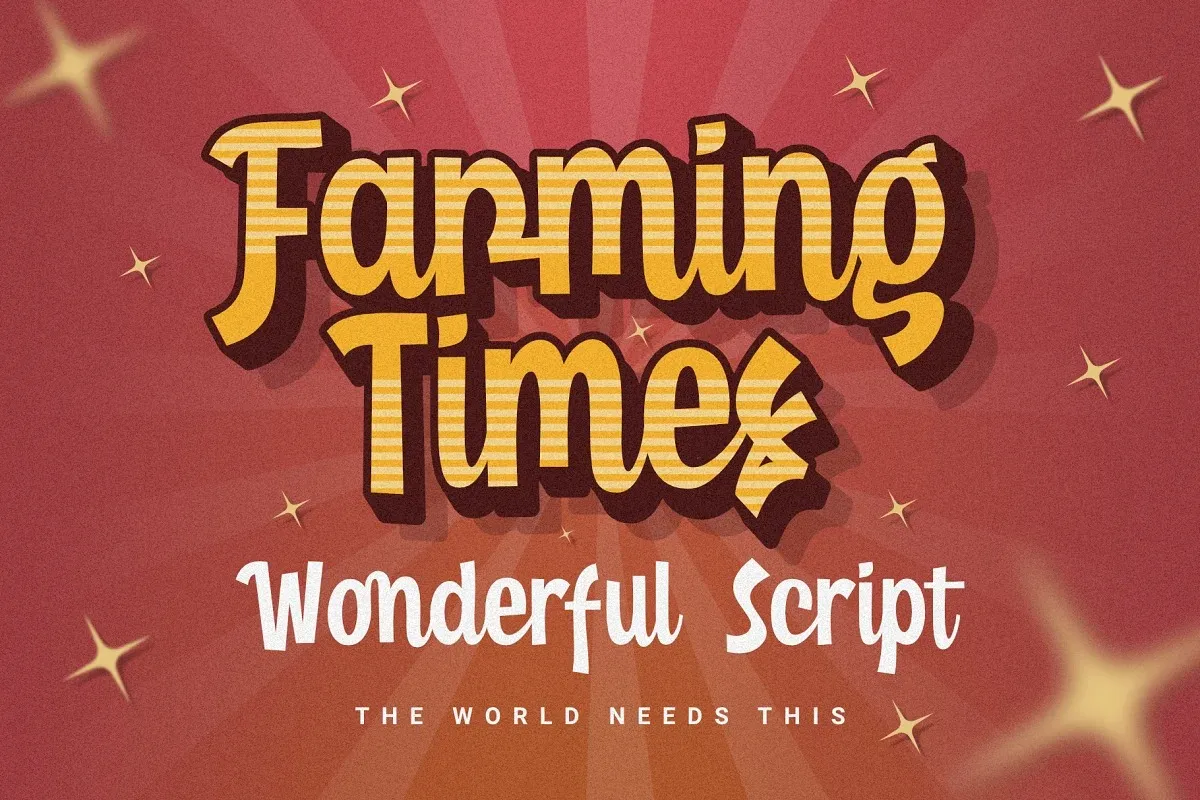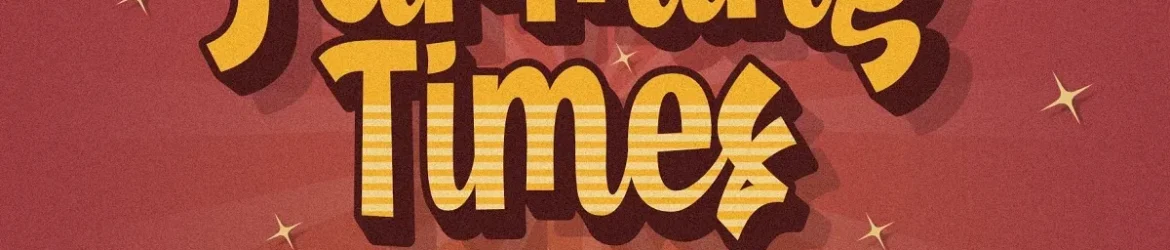
A Farming Times Font é uma elegante escolha para quem busca uma trilha sonora retro e vibrante para seus projetos de design. Este script bold tem um tom nostálgico que transporta a mente diretamente para os anos 60, oferecendo uma sensação calorosa e descontraída às criações. Seu ar colorido e vistoso torna-o perfeito para qualquer projeto onde você deseja destacar-se e criar um impacto poderoso no mundo da design gráfico. Uma fonte que combina a modernidade de um script com o charme vintage dos anos 60, ela se adequará perfeitamente à criação de materiais de marketing, logotipos criativos ou até mesmo ao desenvolvimento de sites web de estilo retro. Seja você um designer profissional ou amante da arte digital, a Farming Times Font tem algo para atender sua necessidade e tornar qualquer projeto uma verdadeira obra de arte.